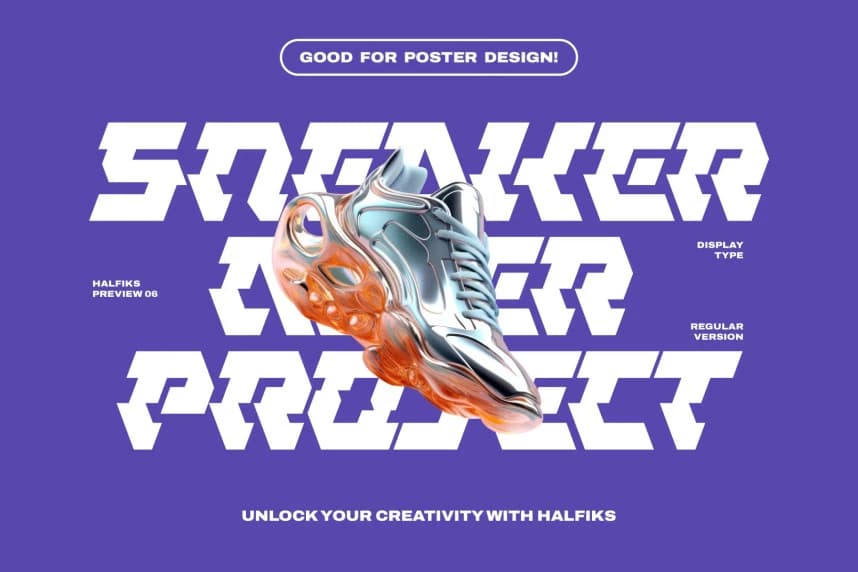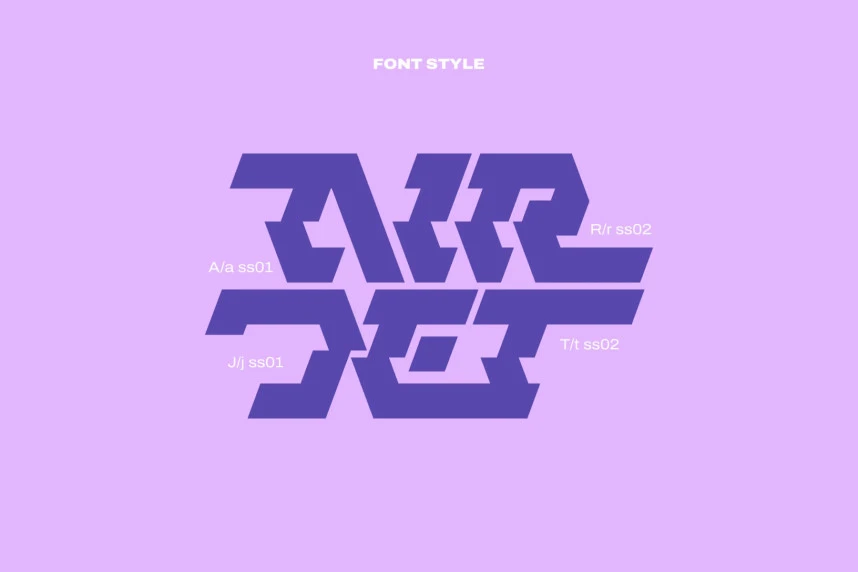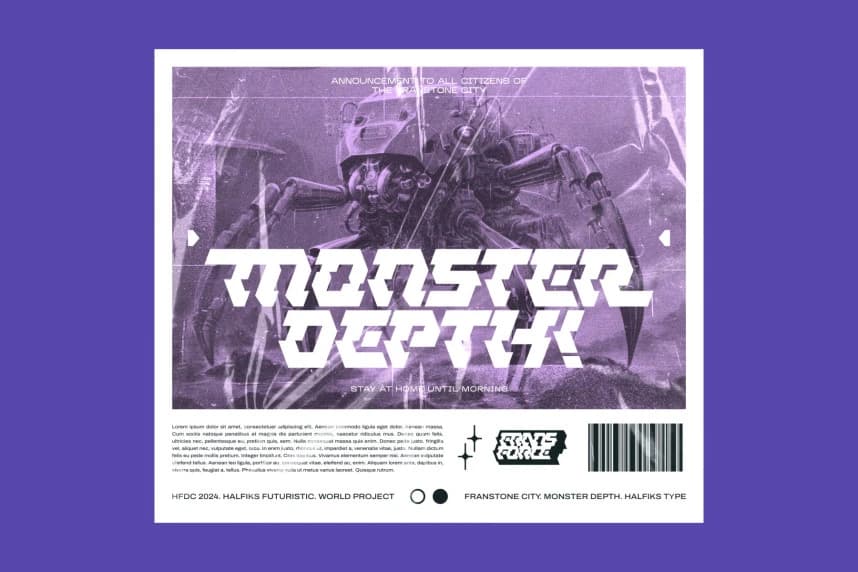
Halfiks Futuristic Font
Halfiks Futuristic Font, deneysel ve fütüristik temelli bir fonttur; geleceğin zarafetiyle ilgili fantastik filmlerden ilham alır. Bu font tüm harfleri büyük harf olarak içerir ve OpenType özellikleri olarak alternatifler ve ligatürler gibi özelliklere sahiptir; bunları keşfedebilirsiniz.
Halfiks Futuristic Font, gelecek hakkında sofistike olan fantastik filmlerden ilham alınan deneysel, futuristik temelli bir yazı tipidir. Bu yazı tipinde tüm harfler büyük harf olarak bulunur ve OpenType özellikleri arasında alternatifler ve ligatürler gibi özellikler vardır; bunları keşfedebilirsiniz.